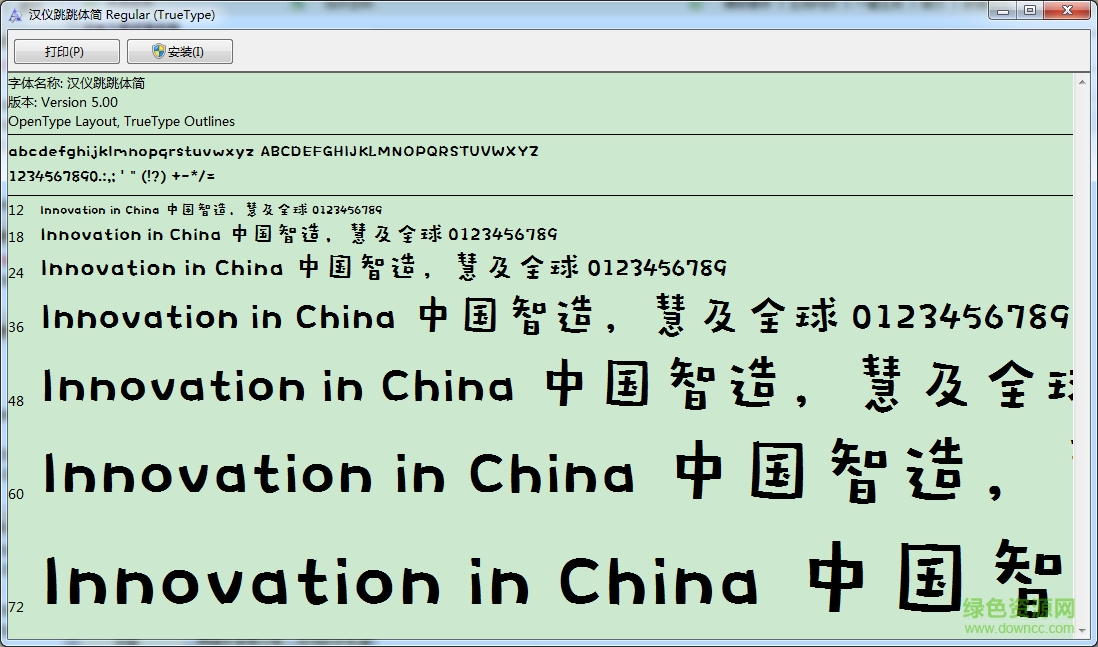
hytiaotiaotij字體又名漢儀跳跳體,是一款非常活潑俏皮的廣告字體,神采生動俊俏,整體感覺天真稚拙,非常好看,喜歡這款字體的小伙伴快來綠色資源網(wǎng)下載吧!
字體造型生動活潑,字形具有童真的感覺,色彩豐富明快,給人以生機盎然的感受。這種個性的字體適用于兒童用品、運動休閑、時尚產(chǎn)品等主題。